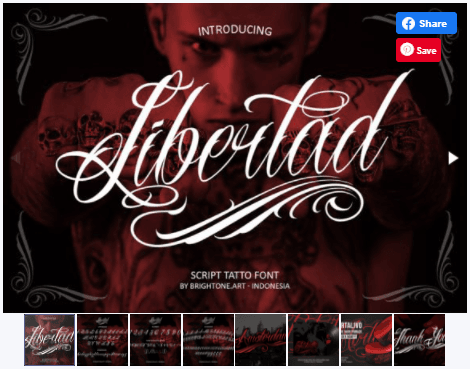
Libertad Font
Libertad - это изысканный и отчетливый рукописный шрифт, мастерски разработанный, чтобы стать настоящим фаворитом. Он сохраняет свои классические каллиграфические мотивы, но при этом выглядит современным и свежим. Влюбитесь в него и доведите свои татуировки до высочайшего уровня!